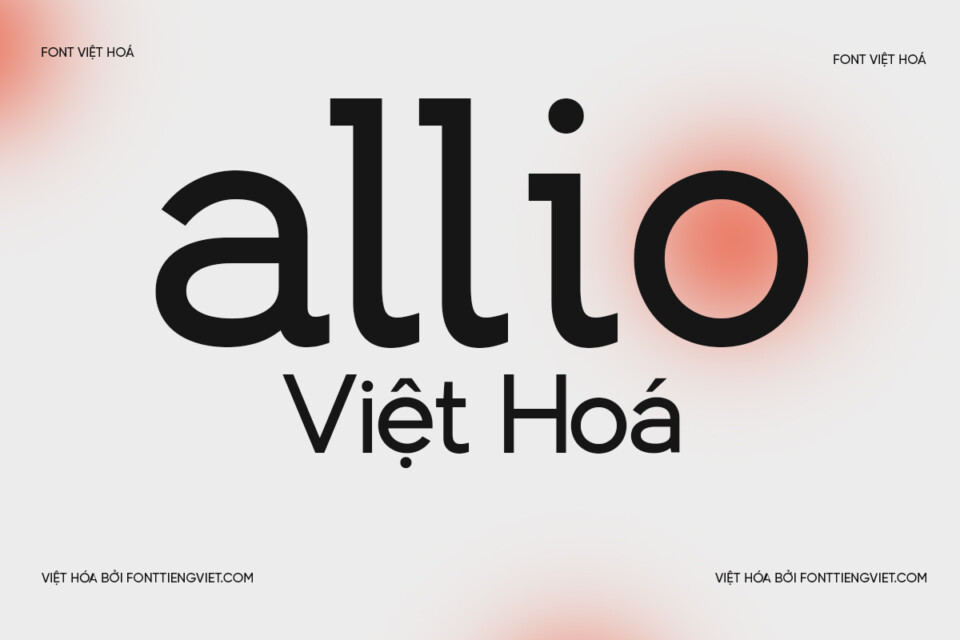
Font Việt hóa 1FTV VIP Allio
Trong thế giới thiết kế đồ họa hiện nay, việc lựa chọn một bộ Font Miễn Phí chất lượng luôn là ưu tiên hàng đầu của các designer. Đặc biệt, bộ Font Việt hóa 1FTV VIP Allio nổi lên như một hiện tượng nhờ phong cách hiện đại, tinh tế và khả năng ứng dụng linh hoạt trong nhiều lĩnh vực khác nhau. Đây là bộ font được tối ưu hóa hoàn toàn cho bảng mã tiếng Việt, giúp người dùng không còn lo lắng về lỗi hiển thị dấu hay các ký tự đặc biệt khi soạn thảo văn bản hoặc làm banner quảng cáo.
Khám phá đặc điểm nổi bật của Font Việt hóa 1FTV VIP Allio
Bộ Font Việt hóa 1FTV VIP Allio sở hữu những đường nét thanh mảnh nhưng không kém phần chắc chắn, tạo nên một tổng thể hài hòa và chuyên nghiệp. Điểm mạnh lớn nhất của bộ font này chính là sự đa dạng trong các biến thể, từ nét mảnh (Light) cho đến nét đậm (Bold), cho phép người dùng tùy chỉnh linh hoạt theo từng mục đích sử dụng cụ thể. Đối với các bạn học sinh và sinh viên, đây là công cụ đắc lực để trang trí bài thuyết trình hoặc làm báo cáo dự án thêm phần ấn tượng và thu hút người xem ngay từ cái nhìn đầu tiên.
Tính ứng dụng cao trong thiết kế đồ họa
Nhờ vào cấu trúc ký tự rõ ràng và dễ đọc, Font Việt hóa 1FTV VIP Allio cực kỳ phù hợp cho các dự án thiết kế giao diện web (UI/UX), làm bìa sách, hoặc thiết kế bộ nhận diện thương hiệu. Các chuyên gia đánh giá cao bộ font này vì nó mang lại cảm giác sang trọng nhưng vẫn giữ được nét gần gũi, thân thiện. Khi sử dụng trong các ấn phẩm in ấn như thiệp mời, brochure hay poster sự kiện, font chữ này giúp truyền tải thông điệp một cách hiệu quả và trực quan nhất. Hơn nữa, việc được việt hóa chuẩn chỉnh bởi đội ngũ 1FTV giúp đảm bảo tính thẩm mỹ cao nhất cho các văn bản tiếng Việt phức tạp.
Lợi ích khi sử dụng Font Việt hóa 1FTV VIP Allio trong học tập
Việc tiếp cận với các bộ font chất lượng như Font Việt hóa 1FTV VIP Allio giúp các em học sinh rèn luyện tư duy thẩm mỹ và kỹ năng trình bày văn bản khoa học. Thay vì sử dụng những phông chữ mặc định đơn điệu, việc áp dụng font chữ mới lạ sẽ tạo động lực sáng tạo trong quá trình học tập. Các thầy cô giáo cũng có thể sử dụng bộ font này để thiết kế bài giảng điện tử sinh động hơn, giúp học sinh dễ dàng ghi nhớ kiến thức thông qua những hình ảnh và chữ viết bắt mắt.
Tổng kết về giá trị của Font Việt hóa 1FTV VIP Allio